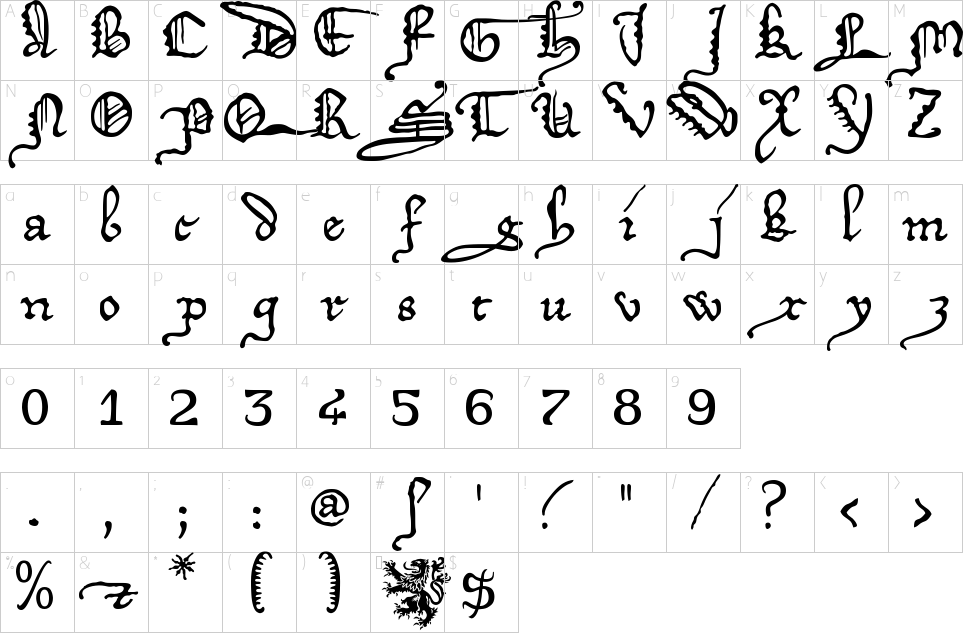
Descubra a beleza única da DeiGratia font, uma elegante escolha para qualquer projeto visual. Ela foi projetada por Pia Frauss e sua simplicidade combinada com detalhes suaves fazem dela uma opção ideal tanto para profissionais quanto para iniciantes. Essa fonte é perfeita para criar textos de alta qualidade, seja em design gráfico, publicações ou até mesmo em design de sites pessoais. Descubra por si mesmo o poder dessa fonte gratuita e facilmente instalável em sistemas Windows e Mac. Com seu formato legível e fácil de usar, a DeiGratia é uma excelente adição à sua coleção de recursos gráficos gratuitos. Agradecemos pela sua visita e esperamos que você aprecie tanto como nós o design desta fonte única.